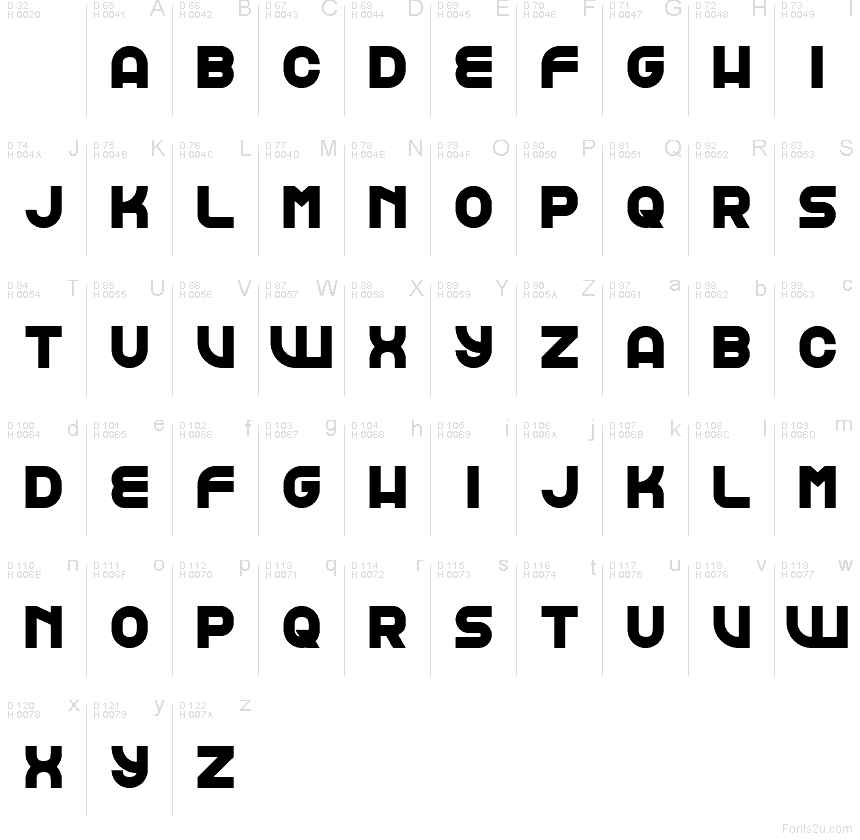
Shock Room od Vladimira Nikolice je bezplatné techno display písmo složené z masivních geometrických tahů a těsně uspořádaných tvarů. Zaoblené tahy a tupé svislice dodávají sazbě industriální, modulární siluetu. Ostré zářezy narušují jinak hladkou konstrukci a dodávají jí mechanický nádech.
Technologie, gaming a elektronická hudba jsou pro toto důrazné písmo nejvhodnějšími oblastmi, díky čemuž se hodí na plakáty událostí, merchandising a digitální grafiku. Jeho předimenzované tvary dokážou utvářet identitu značky, zejména u produktů nebo podniků zaměřených na stroje, zvukové aparatury či futuristickou zábavu.